提起安景臣的名字,爱好设计、喜欢电脑字体与书法艺术的朋友可能并不陌生,十余年前,他的首款电脑字体—安景臣钢笔行书便诞生了。该字体几乎开创了中国手写电脑字体的先河,因为在此之前,鲜有将手写字体编成电脑字库的。字体一发布,各大网站纷纷转载,点击率、下载量遥遥领先。安景臣的名字被更多的人所熟知。字体先后被多家知名企业、公司所采用,但是,真正付版权费的寥寥无几。安景臣把这些看得很淡,这款字体几乎是公益的,对大多数人来说,使用都是免费的,但是社会效应是巨大的,也让更多的人认识了安景臣。
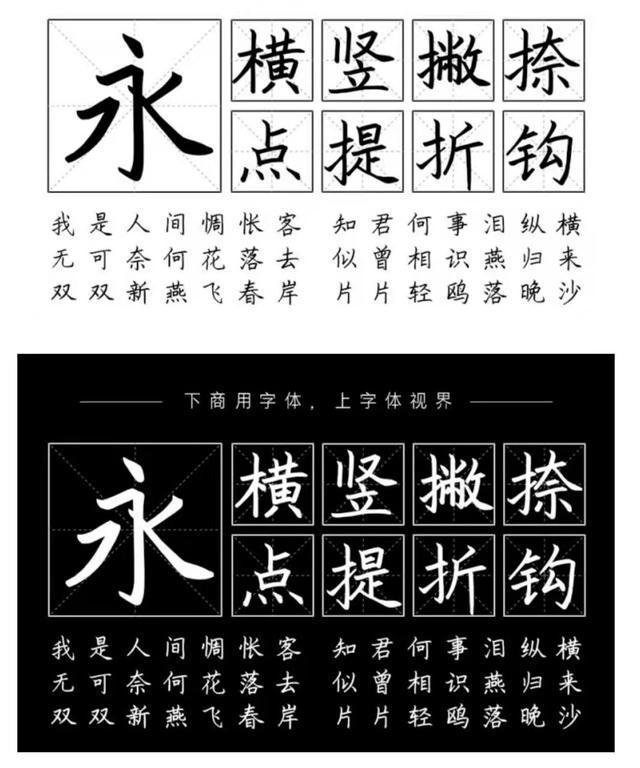
之后,又有安景臣硬笔行书、安景臣硬笔楷书问世,进一步扩大了知名度,其中的楷书字体还被用作学生硬笔字帖专用字体,感到非常欣慰,自己的努力得到了进一步的认可,坚定了他继续从事电脑字体研究的信心。后来,他担任了中国大陆字体字库交流中心副秘书长一职,主要在网上与全国各地的同行交流、学习,研究行业发展。开阔了眼界,增长了见识,他的老师,徐悲鸿纪念馆执行会长、画马传人、著名书画家梁秋生先生也是一位字体专家,他创作的字体—大梁体深受大家的喜爱,影响广泛,社会使用率非常高。从梁秋生老师那里,他学到了许多东西,懂得了学艺先要学做人的道理,同时梁老师在字体设计、书法创作上给予了很多专业的指导,从而引导他在字体设计路上越走越远!
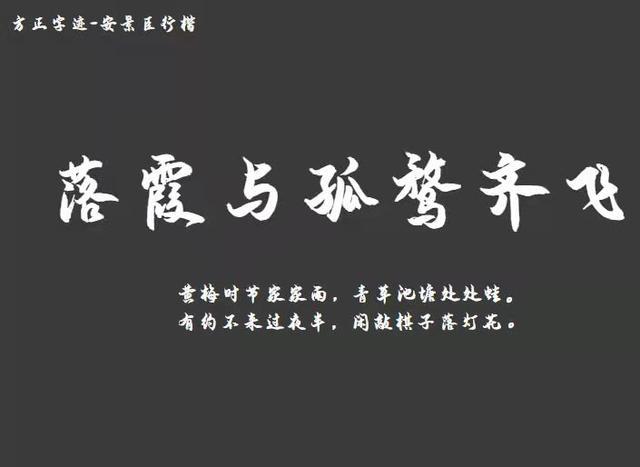
方正字迹——安景臣行楷
后来,在梁老师的引荐下,安景臣与著名新兴字库公司汉标公司合作,推出了一系列手机平台使用的字体与电脑字体,深受好评!字体上手机平台,不是一件容易的事,除了要求书写风格有个性之外,每个手机的型号不同,对字体的要求也不同,要适应每一款手机,就要反复试验,这其中,字库公司付出了很多,同时又要作者全力配合,缺少了任何一个环节,哪怕是一个标点符号的错误,都会被驳回,可见字体上手机平台的难度。好在经过不断探索、磨合,自己的字体终于上手机平台了,陆续有一系列景晨字体上线,自己有了成就感,这是大家全力配合的结果啊!每款字体下载收费3-6元不等,在初期几个月的时间里,每月有一些收入,还算不错的,心里暗暗高兴,但随着手机字体的增多,后续字体跟不上,收入逐渐减少,到现在,甚至可以忽略不计了。但从这个过程中,学到了许多别人学不到的东西,从中体会到了别人体会不到的欢乐!
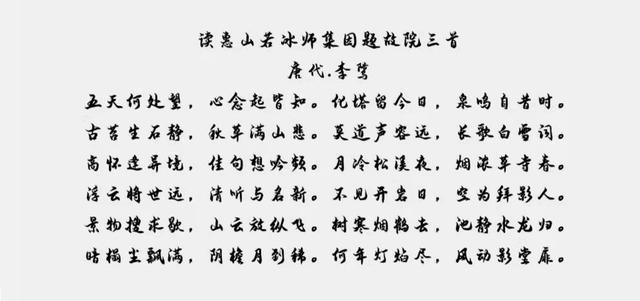
大家知道,北大方正是中国制作电脑字库最专业的厂家,能在北大方正制作一款字库,是一生值得荣耀的事情。但是,北大方正对字体的要求也非常高,一般人很难入编的。著名书法家也仅有启功、舒同、刘炳森等少数大师级人物的字体入编,可见入编之难度。入编北大方正字库,字体一方面要有艺术性、另一方面要雅俗共赏,同时还要有个性特点,有自己的风格特色,因此,符合条件的书法家也不多。安景臣十余年前就有入编北大方正字库的想法,曾参加字体设计大赛并获奖,但因种种原因,字体未入编字库,之后,他一直未放弃这个梦想,多次投稿,最后,一颗诚心感动了上帝,他的字体终于入编了!入编北大方正字库,也许是他字体事业的一个里程碑,虽然目前未真正带来实际经济效益,但关注他的更多了,他决心在字库事业上继续努力,创造新的成绩!
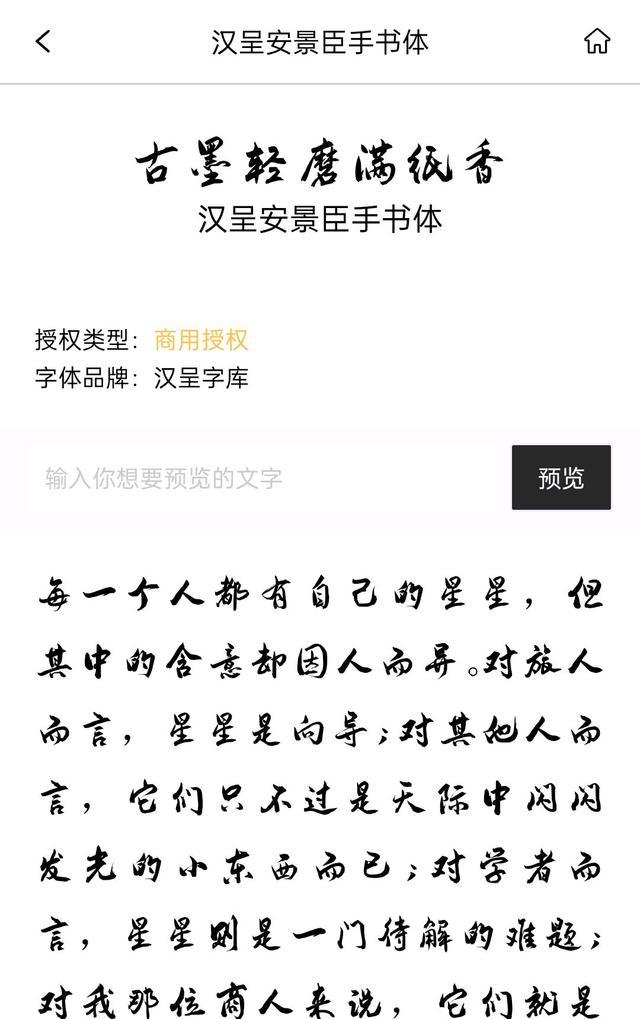
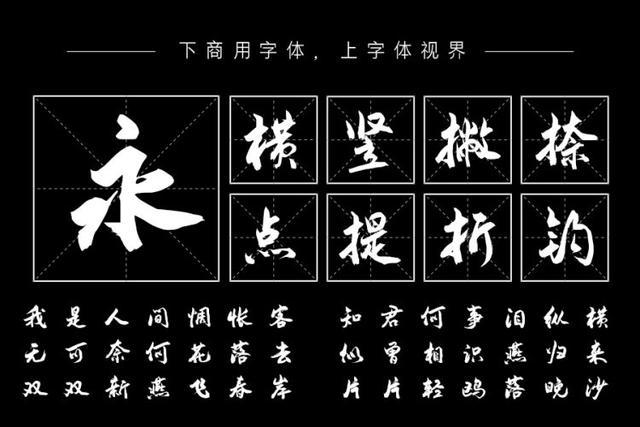
汉呈安景臣手书字体欣赏
后来,他又和汉呈字库公司开发有汉呈安景臣行书繁体字库,汉呈安景臣手书体等,为普及传统书法文化做着自己的贡献!他现在正在探索自己编字库,这在从事书法的人来说,可以说凤毛麟角。手机平台字体就是他自己书写,采用专用软件生成的,后期经过专业公司调整上线的。他的最新毛笔行书字库,安景臣手书体是一款独立书写,与汉呈字库公司合作开发的字库。安景臣的目标是创作出更多、更好的字体,为中国字体事业的发展做出更大的贡献!这需要志同道合的人一起努力,也希望有和他同样梦想的朋友联合起来,一起圆梦,共同弘扬传统书法艺术,做无愧于时代,无愧于后人的事,共同为字库事业的发展而努力!
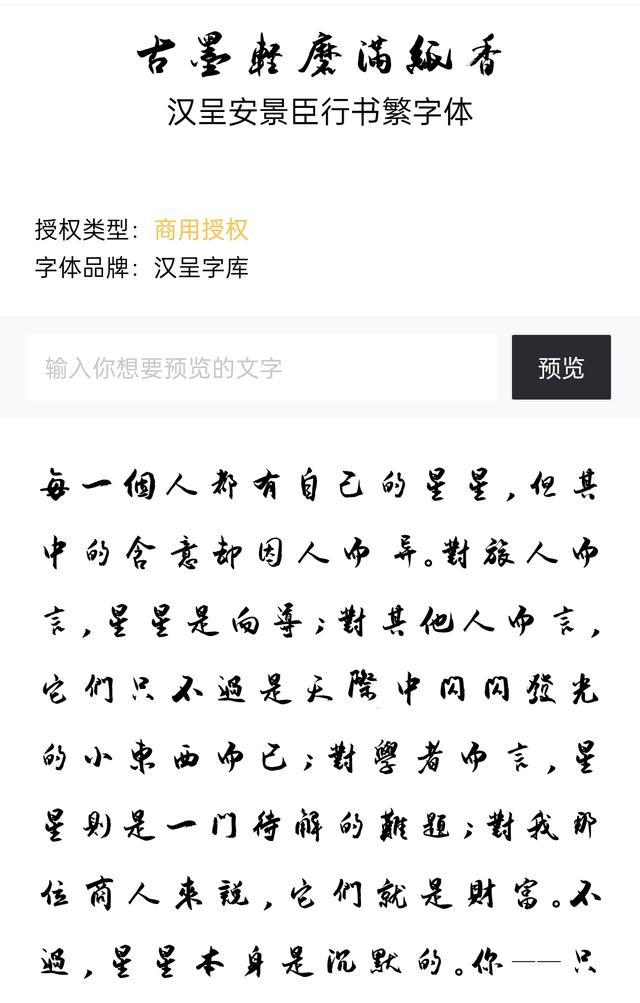
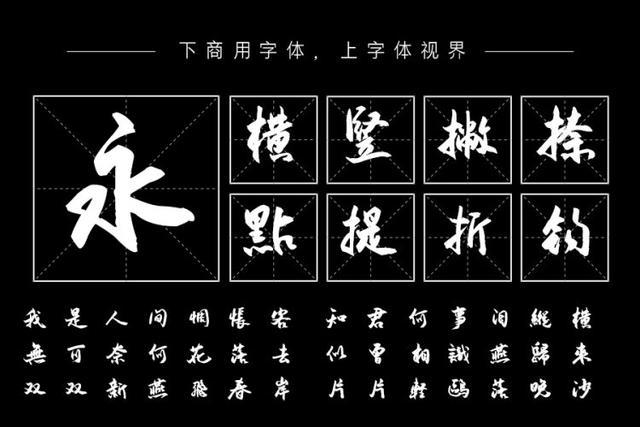
汉呈安景臣行书繁字体欣赏
安景臣除了在字库方面取得了一定的成绩,书法上也是软硬兼施、诸体皆能。在做字库前便是小有名气的硬笔书法家,获得了很多奖项,并入编作品集、大辞典等。但安景臣把这些看得很淡,也很少参与书画类商业活动,但是一些公益性活动经常见到他的身影,他用自己的方式,弘扬传统艺术,帮助弱势群体,受到了社会认可。
安景臣先生获奖证书
安景臣不但擅长楷行隶篆草,五体皆能,而且能左右手书,书写反字、对各种风格美术字也是信手拈来,只是很少展示,他说那些都是雕虫小技,不值一提。其实,人们常说,书法功夫在书外,安景臣除了书法外,对于文学写作、诗词歌赋、歌词创作、篆刻艺术、国画山水、声乐艺术等皆有研究,且取得了不俗的成绩!曾作诗:“前人精髓需继承、博览群书取真经。推陈出新为我用,独开一派立新风”。他是这样写的,也是这样做的,不但专研书法知识,还研究姊妹艺术与传统文化,但是师古不泥古,不墨守陈规,敢于突破传统束缚而自成一派,受到了社会的认可。获得过各级奖项,得到了权威部门的认可。其中,书法作品参加过世界和平清华大学书法展、被铁人纪念馆、大庆博物馆等收藏。获得过北京写作学会一等奖,歌词作品获大众音乐学会银奖、声乐获艺术中国黑龙江赛区银奖等。一个人在一个领域取得成绩已属不易,何况这么多领域呢?实属难得!但安景臣对此却谦虚地说:“其实艺术都是相通的,学好做一件事,就学会了做一切事”正是他懂得了转益多师、触类旁通,才使他在艺术的海洋里左右逢源,无往而不胜!
虽然取得了这么多成绩,但他本人非常低调,他说:他的主业还是书法,其他艺术都是为书法服务的。一个人一定要做到一专多能。一专,指的是一定要有自己的主业,多能,指的是其他爱好,喜欢的门类都要围绕着这个主业。如果除了写字,什么都不会,那是书奴,写出的字必然没有神采,而如果一个人什么都会,研究书法也只能是泛泛而谈,不能深入。他还说:当今社会,为书法家提出了新的课题。古代宣纸的发明,为书法作品的流传提供了载体,成为了可能。然而纸张保管不易,后来又出现了碑刻,自从有了碑刻,一些名碑得以流传,书法艺术百花齐放,异彩纷呈。而如今,电脑网络的出现,为书法艺术的传播与发展提供了更为便利的条件,让书法艺术的发展插上了翅膀。古人说:笔墨当随时代。作为新时代的书法家,有责任、有义务承担重任,让书法在网络的普及下大放光彩。书法与电脑字库的结合就是互联网+应用的典型案例。这些年安景臣一直在朝着这个方向努力,视字体的美学研究、另一方面是国外的知识产权相对完善,人们以侵权盗版为耻。而国内,许多人不知何为侵权盗版,有许多侵权行为都是无意的,也有许多是有意的,但由于法治不健全,侵权者很难得到惩治,这也是侵权盗版屡禁不止的原因。基于以上原因,书写制作字库者没有动力,靠字库无法维持生计,不能形成良性循环,长此以往,这个行业很让人担忧。好在社会大环境越来越重视版权了,相信会越来越好的,希望有识之士重视起来,共同为中国文化的发展献计献策,为字库行业的繁荣尽心尽力!
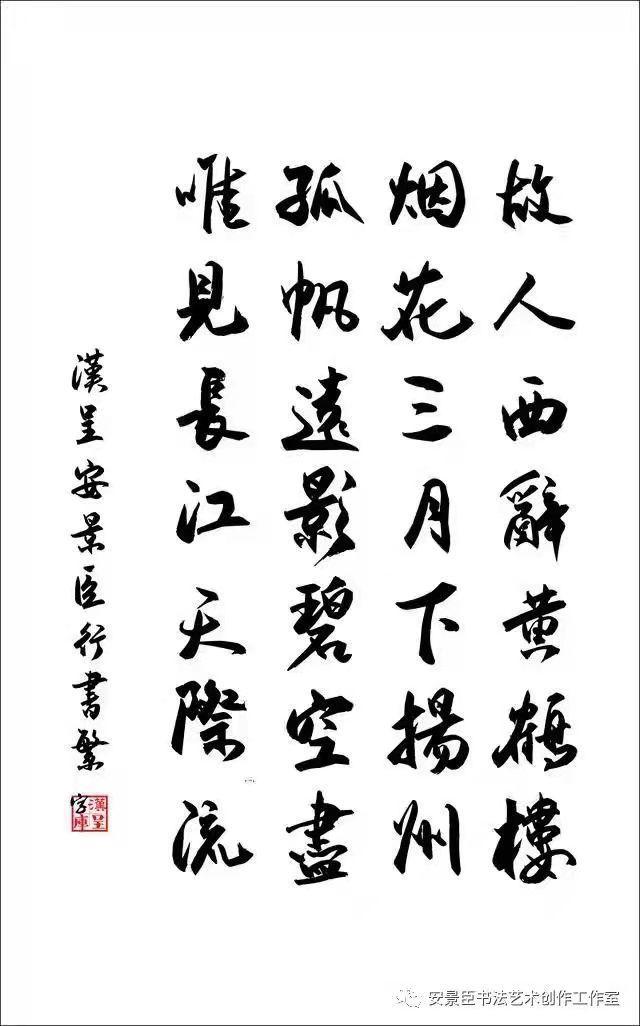
汉呈安景臣手书体欣赏
安景臣先生获奖证书
安景臣先生书法欣赏